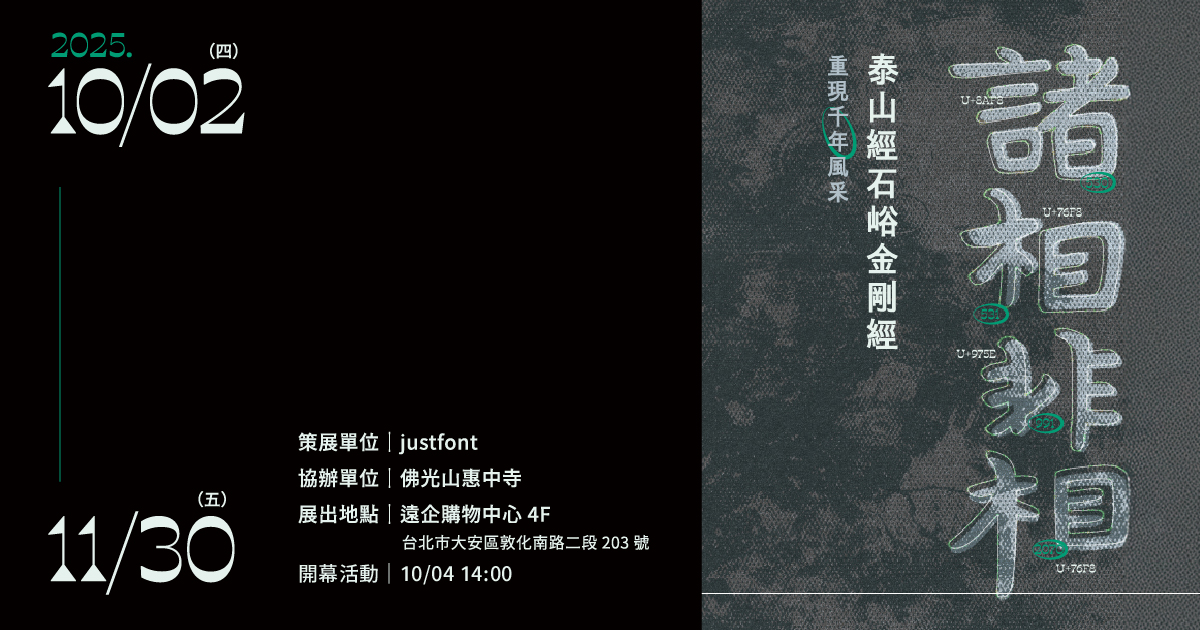
諸相非相|泰山經石峪金剛經——重現千年風采
在泰山山腳的河床上,刻有一部千年佛經:《泰山經石峪》金剛經。這部作品誕生於北齊年間(距今約1400年),相傳為高僧安道一所刻,每字約半米見方,鋪滿近兩千平方公尺的溪床上,氣勢雄渾磅礴。
2022年,justfont 受佛光山委託,要以泰山經石峪的書法風格重現《金剛經》全文共 5,157字,並以銅雕形式安裝於台中新惠中寺大雄寶殿兩側牆面。
為確保可以忠實還原這部經典,台灣字體設計公司 justfont 團隊蒐羅大量拓本交叉比對,並與佛光山密切合作,逐字檢視,嚴謹考究。